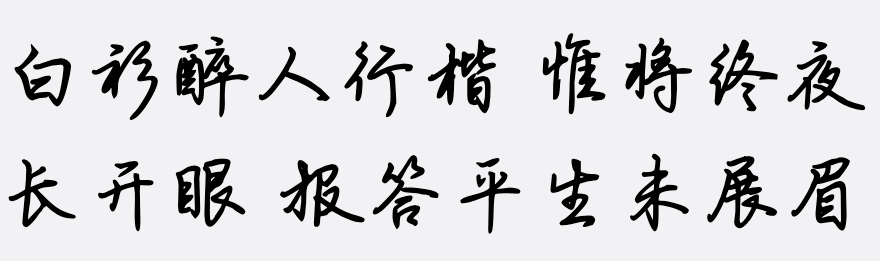
《Aa 白衫醉人行楷加粗》字体的行笔走势连贯,如行云流水,让人感受到一种自然流畅的美感。
整体婉转灵动,散发出一种别样的文艺气息。字体的曲线和线条流畅自然,仿佛每一个笔画都蕴含着一段故事,使文字呈现出一种温柔而充满生命力的感觉。这种婉转灵动的特质使得文字不再只是工具,更像是一种艺术表达的媒介,让人们在阅读和欣赏文字时,能够感受到一种深层次的情感共鸣。
《Aa 白衫醉人行楷加粗》以其独特的行笔走势、提笔有力和整体婉转灵动的特质,成为了众多设计师和文艺创作者钟爱的选择。